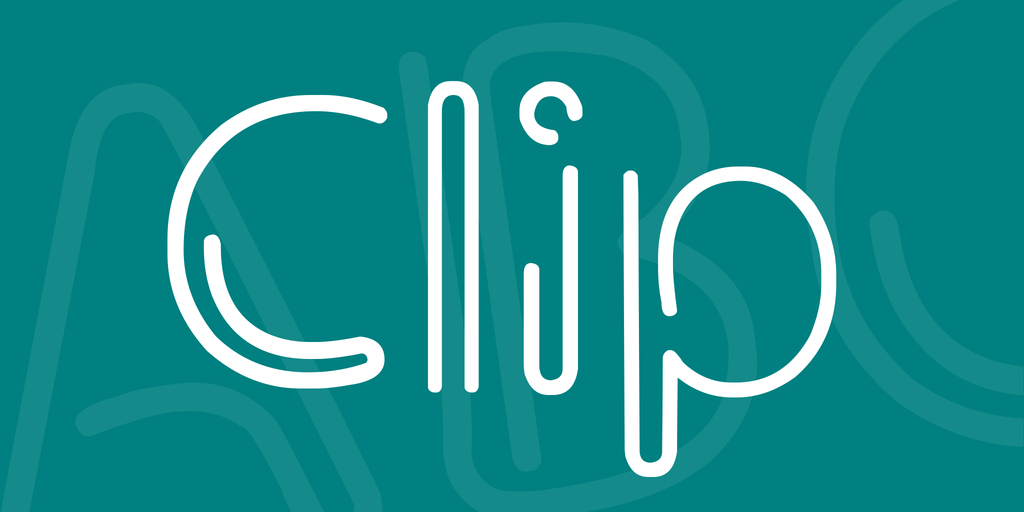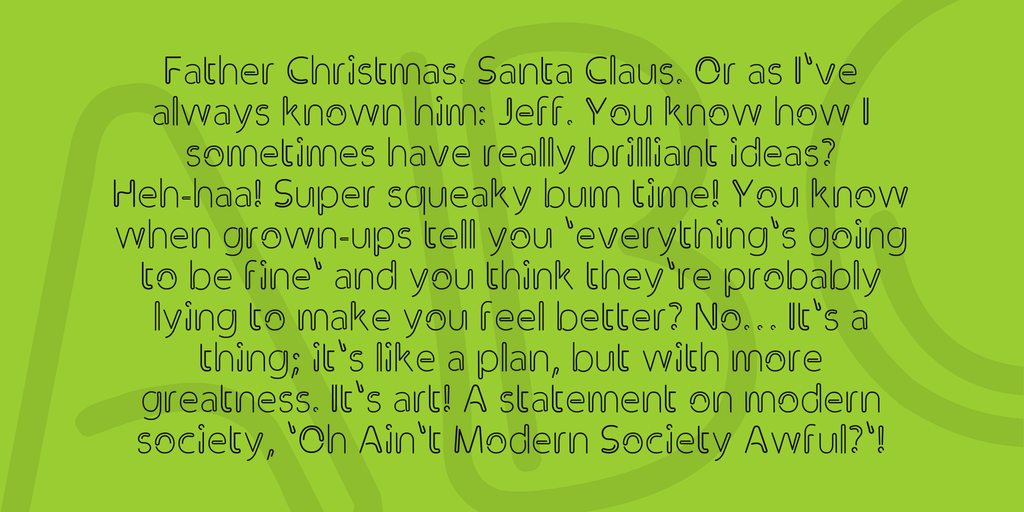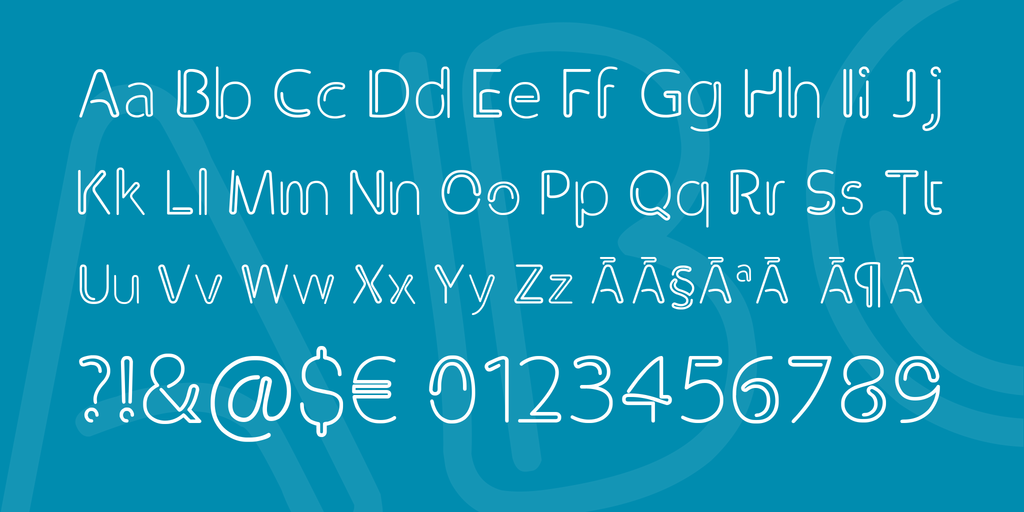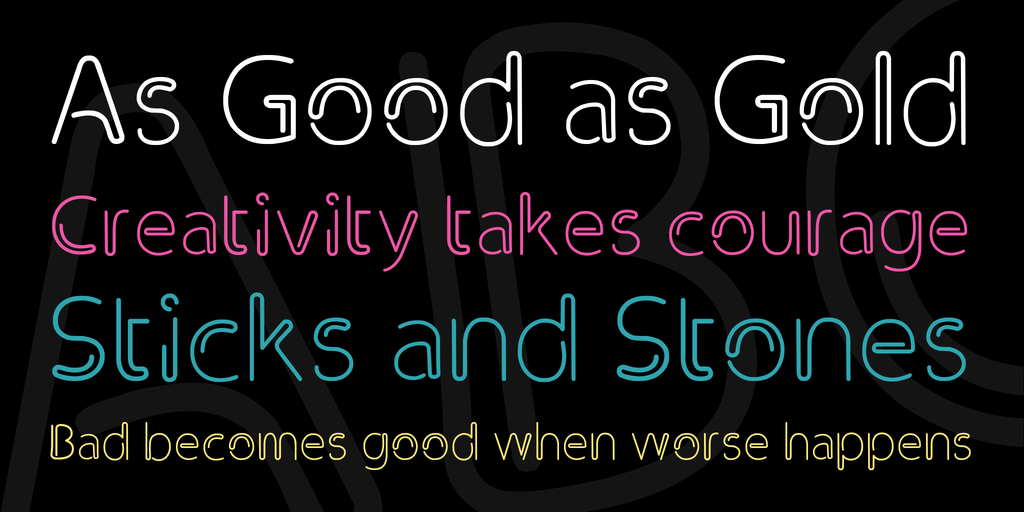
Clip Font
Clip Font Made by Martín Argüello
Mi primer tipografía, inspirada en un clip, intenta los diferentes caracteres con un único trazo y con un rasgo de trazo doble para mantener el estilo común a todos.